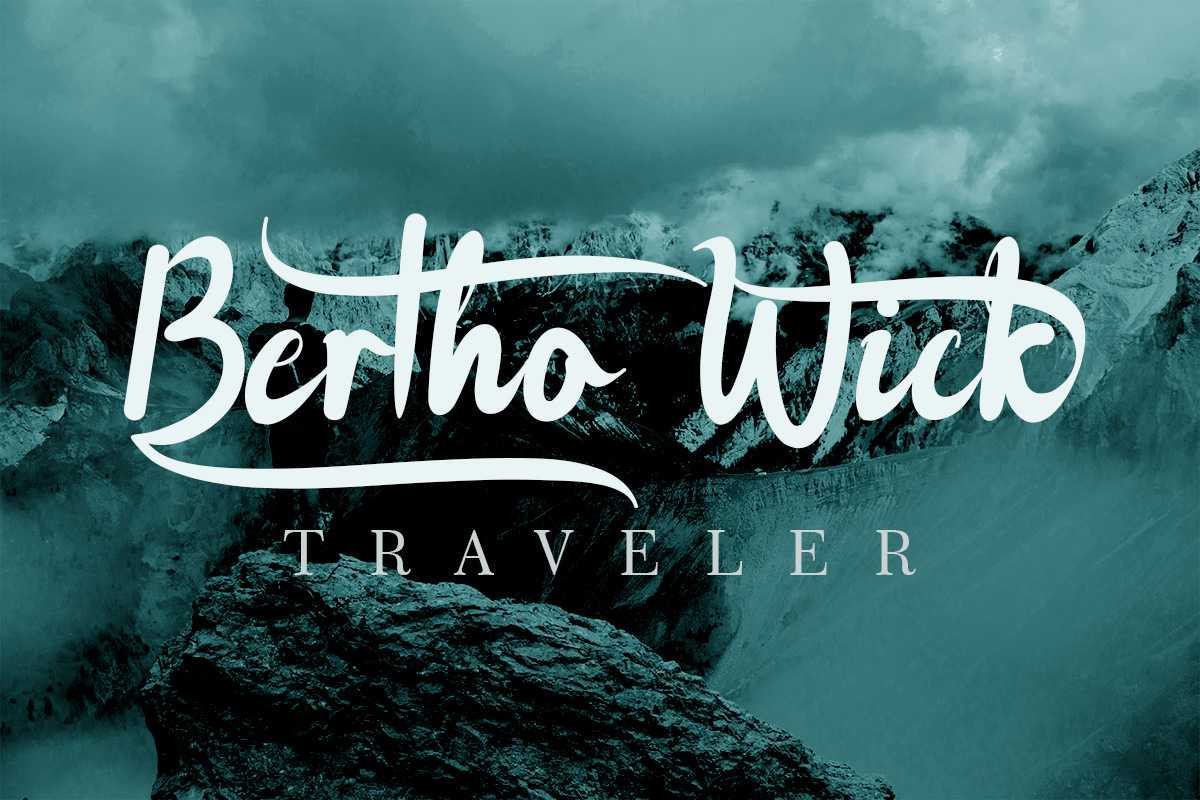
此款香水名为“TheBrilliant”。Briliantis是一种非常独特且适用于所有用途的时尚品牌。我将此款香水命名为“TheBrilliant”,因为我已经找到并创造了满足您所有需求的香水。此款香水可用于您喜欢旅行的人,与你的伴侣一起捕捉美丽的时刻。运河有助于创造目标和品牌。它非常适合在社交媒体上捕捉浪漫故事,也适合在婚礼上写作,如婚礼组织者,婚礼摄影和其他。这款香水被命名为“The Brilliant”。Briliantis是一款非常独特且适用于所有用途的时尚香水。我为这款香水命名为“The Brilliant”,因为我已经发现并创造了满足您所有需求的香水。这款香水可以用于您喜欢旅行的人,与你的伴侣一起捕捉美丽的时刻。这有助于创造目标和品牌。它非常适合在社交媒体上捕捉浪漫故事,也适合在婚礼上写作,如婚礼组织者、婚礼照片和其他。